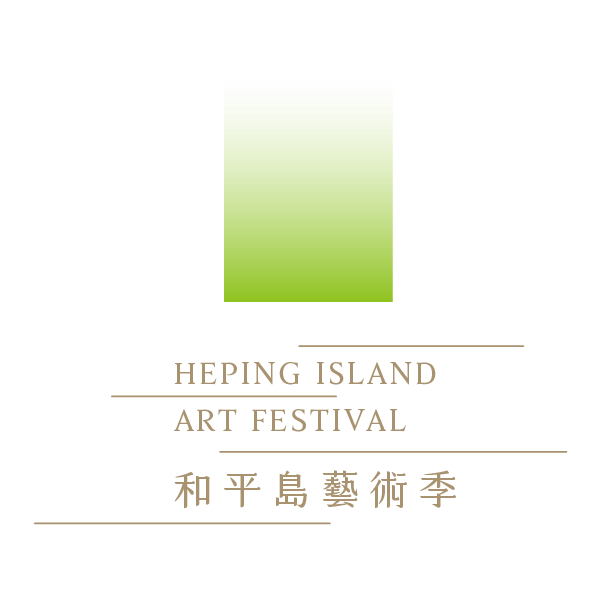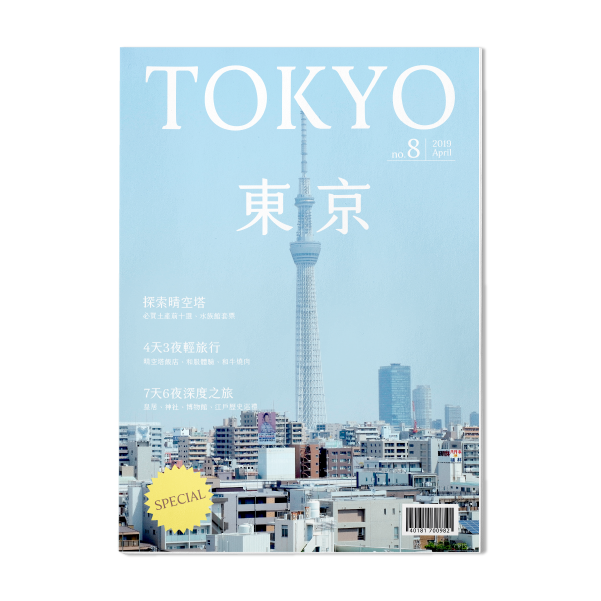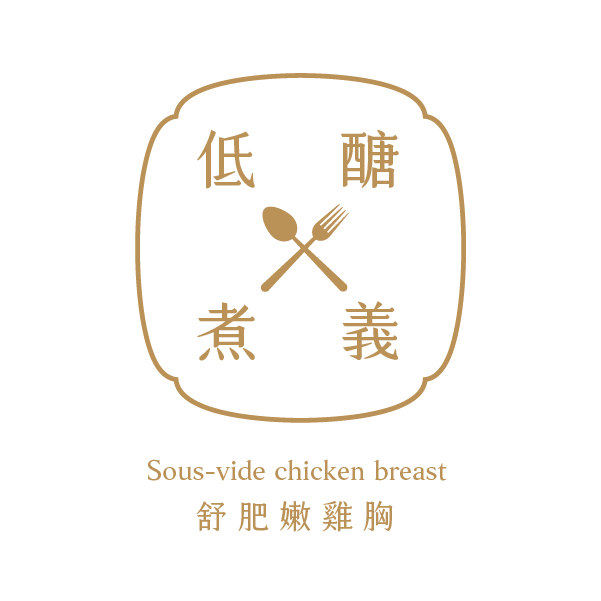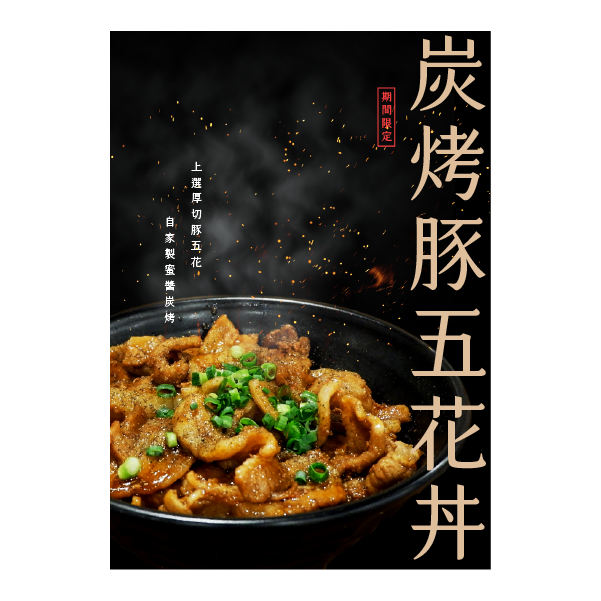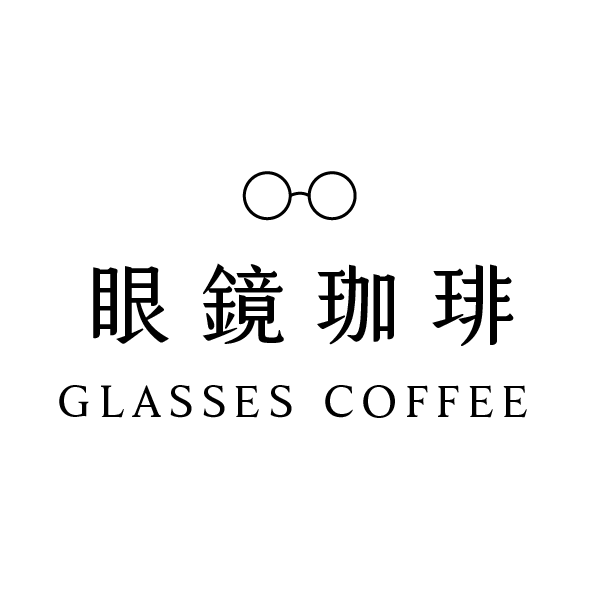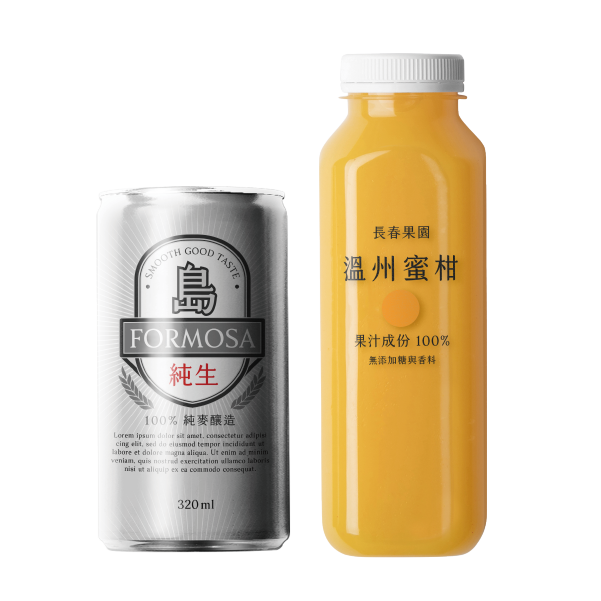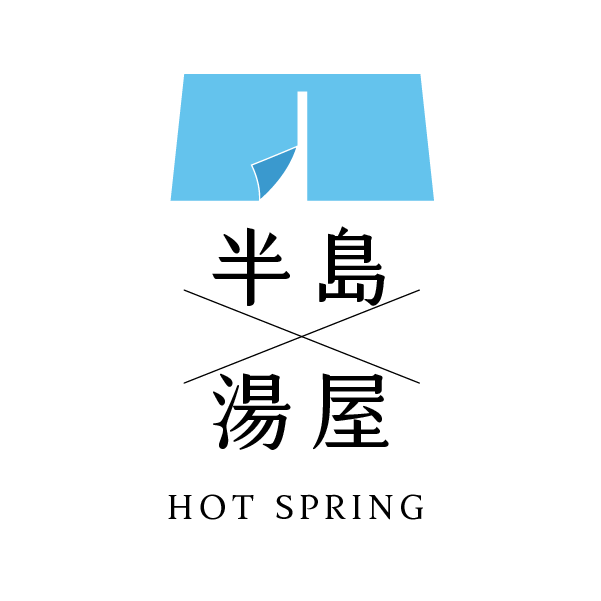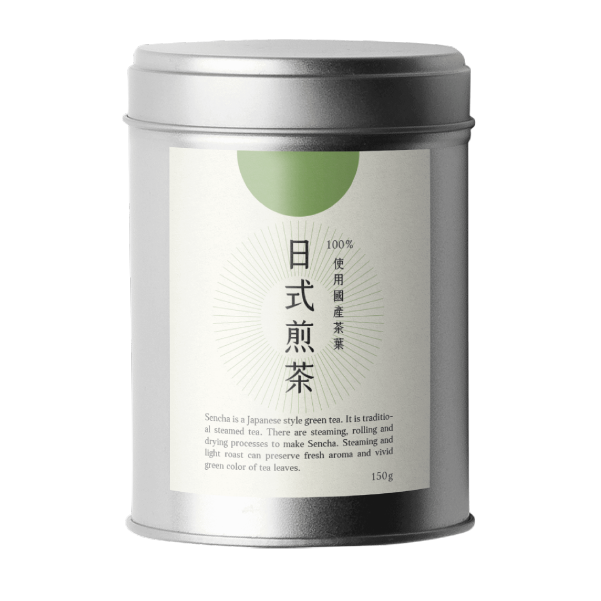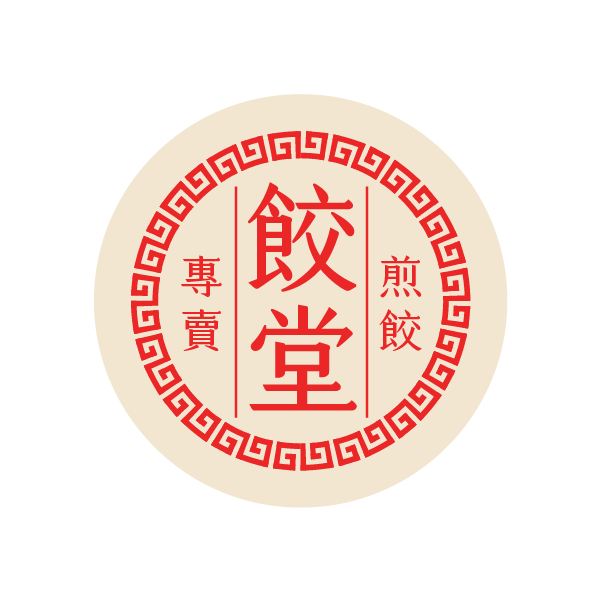
凝書體
源自生活,簡單即美的新字型。
以明體骨架為基底,融入楷體的書寫筆韻,
橫筆尾端如凝霜般翹起,呈現出清爽乾淨的感受。
字型設計師
施博瀚
擅長品牌企劃、識別設計、標準字設計。作品曾獲金點概念設計獎年度最佳設計、DFA亞洲最具影響力設計獎等,並相繼收錄於多本設計刊物中。現為 Bohan Graphi© 設計工作室負責人、中文字型「凝書體」創作者。著有《LOGO設計研究所》一書(如何出版)。